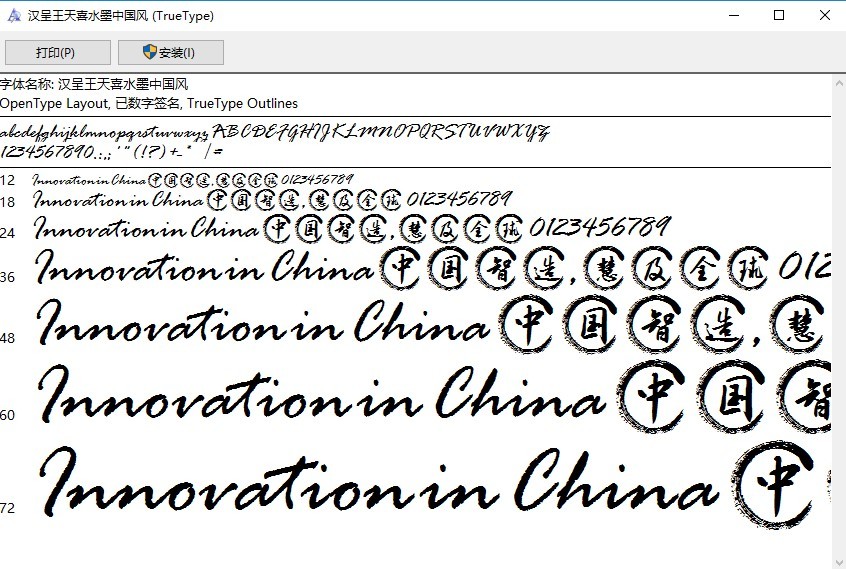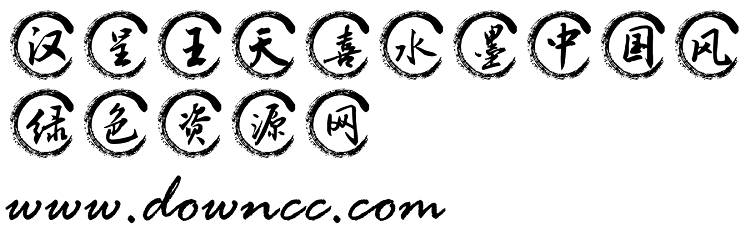
汉呈水墨中国风字体
汉呈水墨中国风字体免费版是汉呈王天喜系列相关的一款字体,在原来的基础上添加了一个水墨风格的圆圈,字形看起来比较浑厚圆润,充满水墨中国风特色,极具个性,是很多用户常用的艺术手写字体,适用于多个不同的设计领域!
汉呈水墨中国风字体简介:
汉呈水墨中国风字体是一款适合手写艺术和广告设计的字体,是汉呈王天喜系列的手写字体。